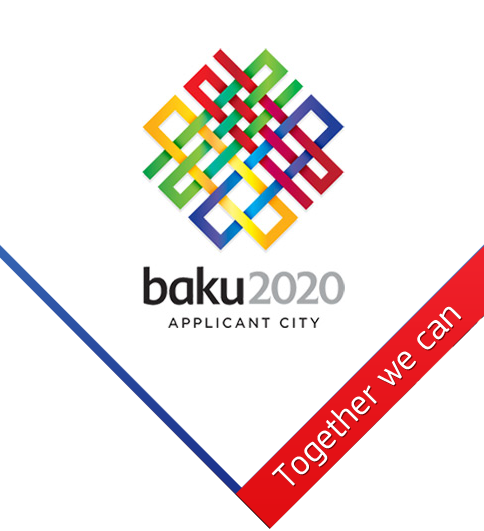
Olympia in Baku 2020 - Schrift gesucht
Es ist eben ein Logo. Die Chance ist groß, dass es entweder eine modifizierte Schrift ist oder dass die Buchstaben sogar speziell für das Logo gestaltet wurden. Falls es noch weitere Anwendungsbeispiele gibt (z.B. in Überschriften), wäre es gut, diese zu sehen. Dann könnte man eventuell mehr sagen.